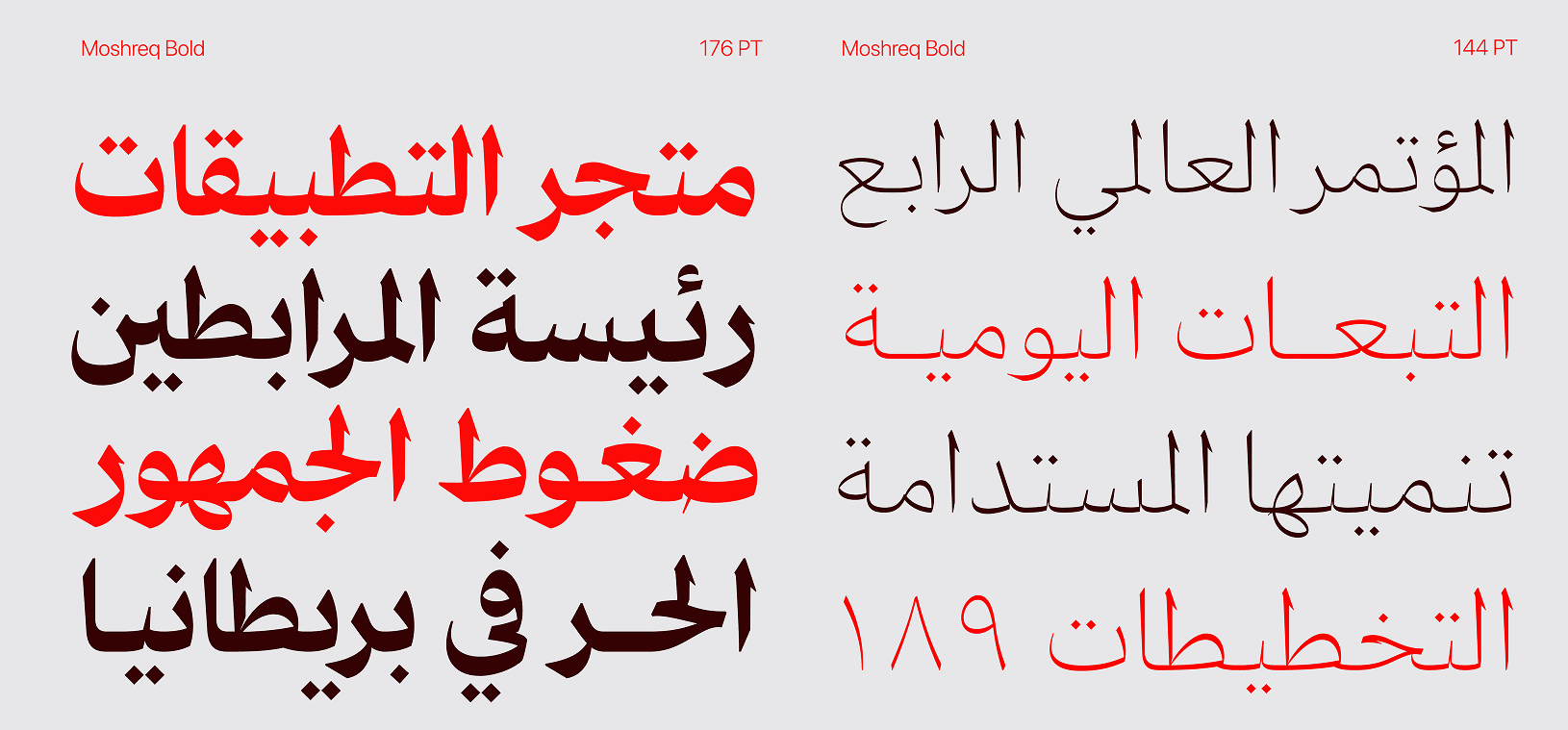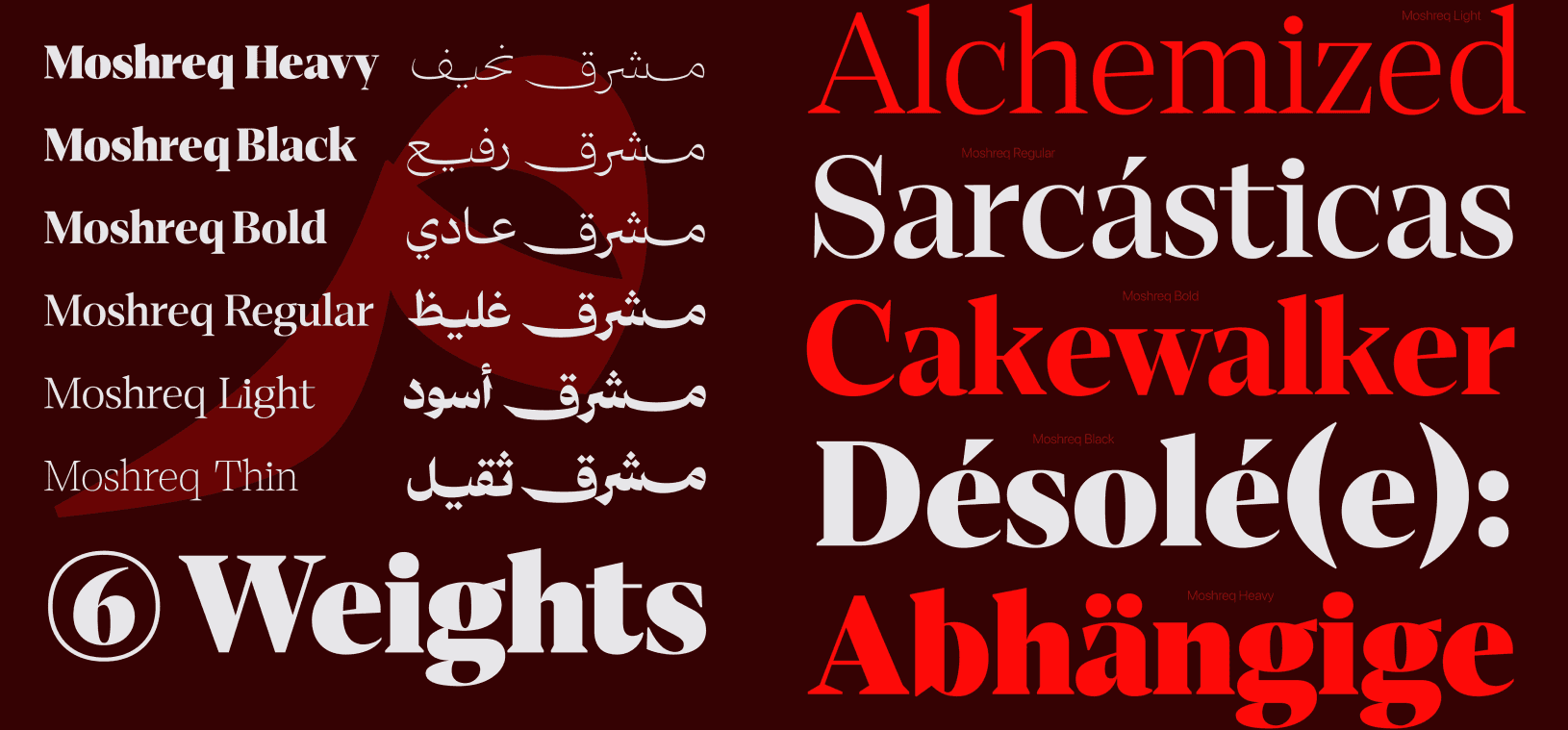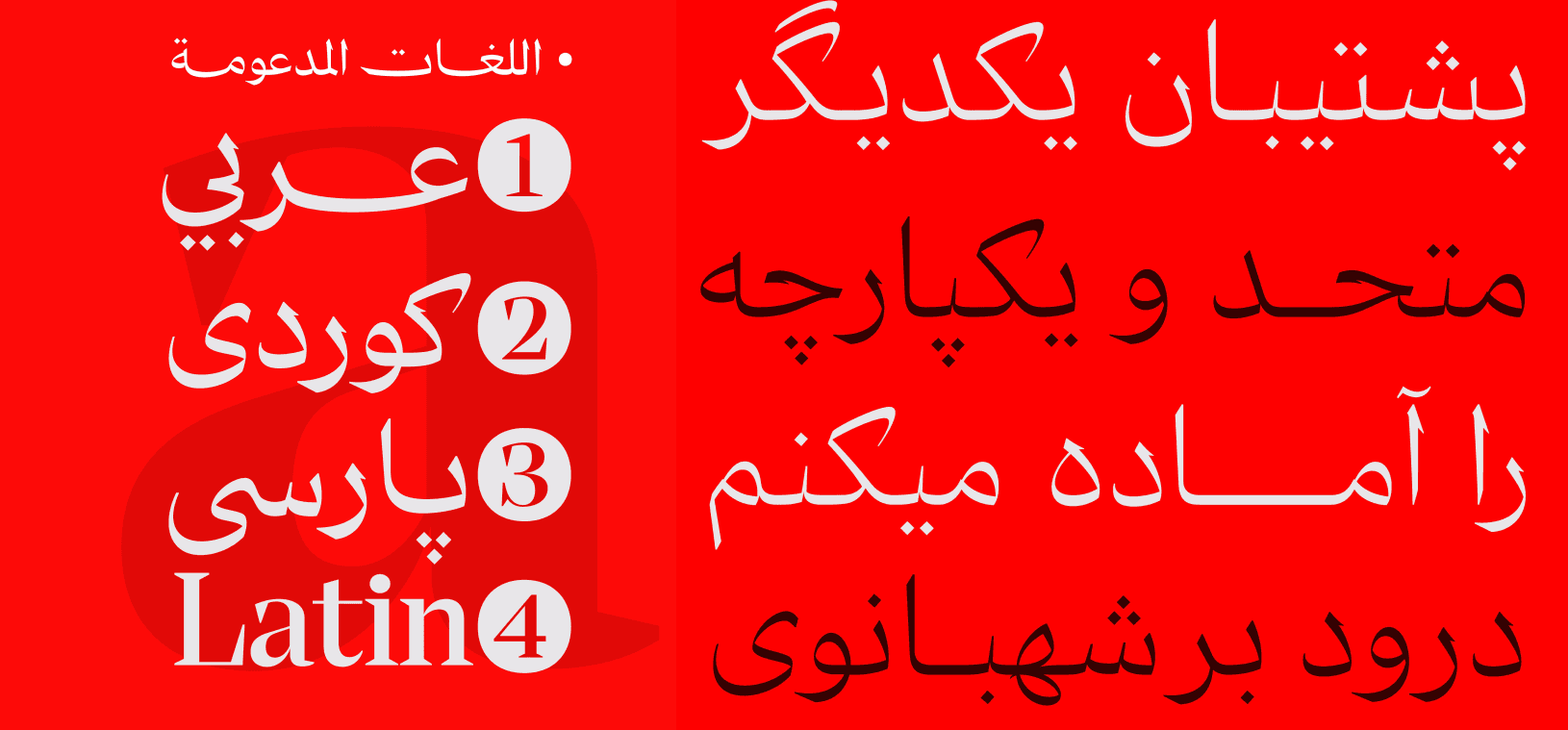
قام محمد هادي برسم خط "مشرق" في أوائل عام 2022 كعائلة عرض أنيقة تتكوّن من ستة أوزان باللغة العربية فقط.
وفي عام 2023، واصل محمد هادي العمل على أشكال الحروف اللاتينية وأنشأ إصدارًا موسعًا.
يحتوي "مشرق برو" على العديد من ميزات OpenType وخمس مستويات من الزخرفة الخطية الأنيقة بأسلوب الكشيدة / التطويل الخطي.